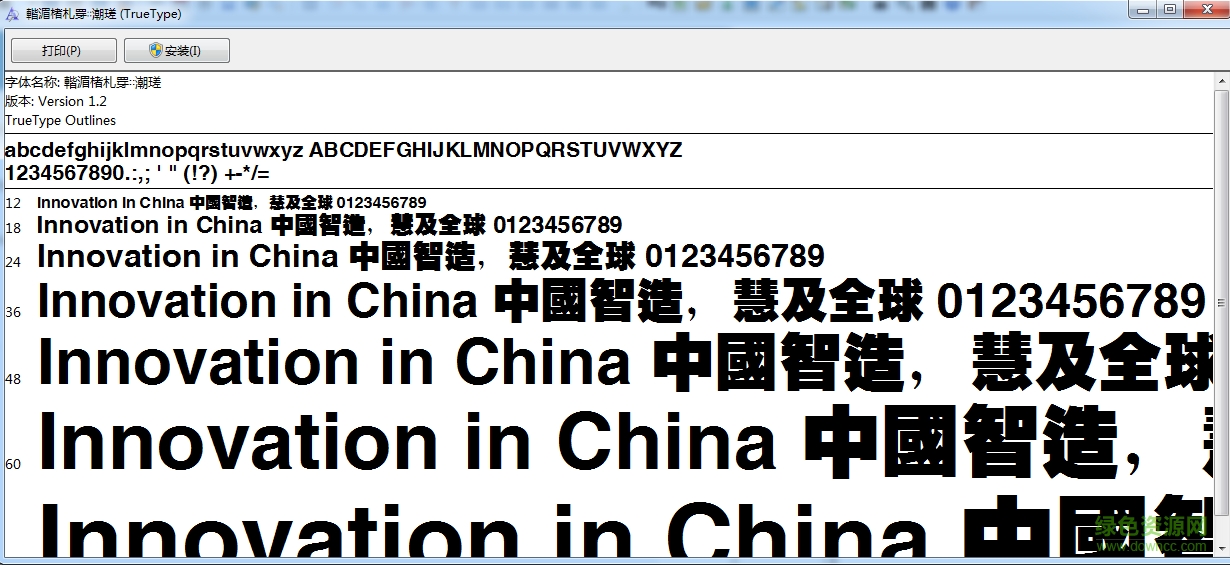
by jossq dmf in beijing字体
byjossqdmfinbeijing是什么字体?by jossq dmf in beijing字体是一款支持中英文输入的汉鼎字体,字型粗黑醒目,用作宣传标语非常适合,需要的朋友们快来绿色资源网下载吧~!
黑体字体特点
无论是西文中的无衬线体/衬线,还是中文的黑体/白体,都有一种直接将笔画变粗的变体,实际上准确的称呼应该是“粗体”(bold),但是很多非专业人士习惯上也被称为“黑体”,造成了中文指称的混乱。在电脑最常用的字处理软件中,通常都可以通过按 B 按钮就将指定文字变为粗体。这种所谓的粗体,只是字体的一个子集,宋体字也可以有粗体,不应该和字体的“黑体”混淆。